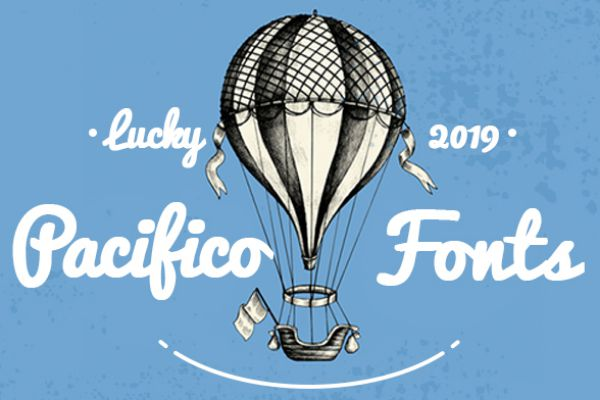
字由好看的免版权英文字体推荐
Pacifico
Pacifico 是一款经典手写体笔画圆润、连贯且富有弹性,给人一种轻松、随意、充满活力的感觉。
非常适合休闲品牌、咖啡馆 Logo、社交媒体标题、节日贺卡。
Camar
Camar 是一款装饰性艺术字体,具有浓郁的复古感,线条粗细均匀,带有几何构造感。它通常表现出一种 20 世纪中叶的现代主义风格,既专业又具有设计感。
Poppins
Poppins 是一款几何无衬线体,它的圆形构造非常完美,无论是极细还是极粗的字重,都保持了极高的易读性和美感。广泛用于 UI/UX 设计(网页和 App)、企业 PPT、说明书正文、极简风海报。
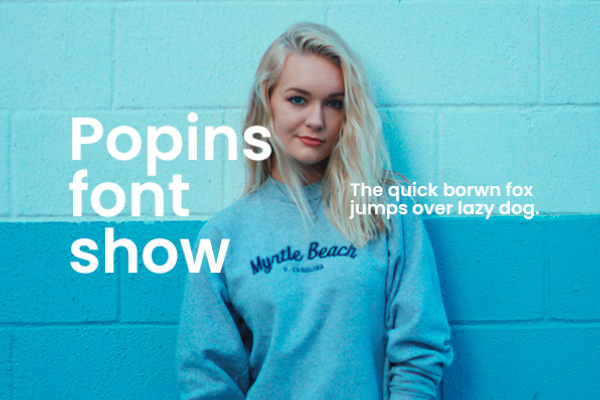
Daizen
Daizen 这是一款具有现代感的显示字体,粗细线条对比强烈,字形优雅、锋利,带有一种高端定制感和时尚气息。
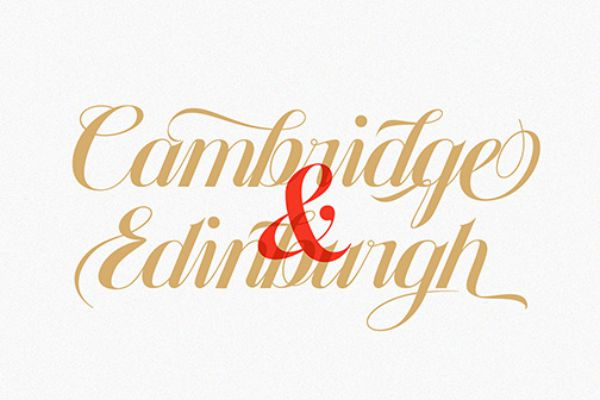
BOXING
BOXING 是一款硬朗标题体,灵感来自拳击海报。字形窄而厚重,充满力量感和压迫感,视觉冲击力极强。
应用场景: 体育竞技海报、健身房品牌、强调力量和速度的广告语、震撼性的视频封面。